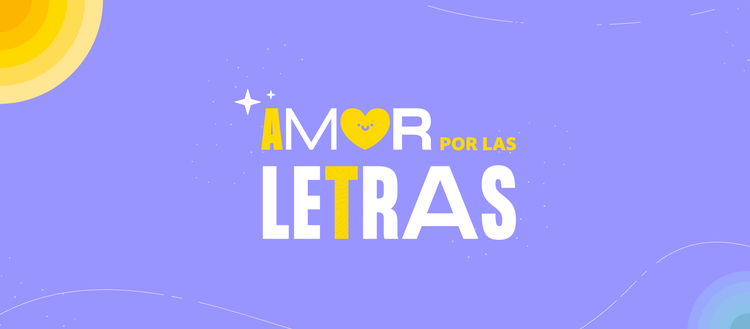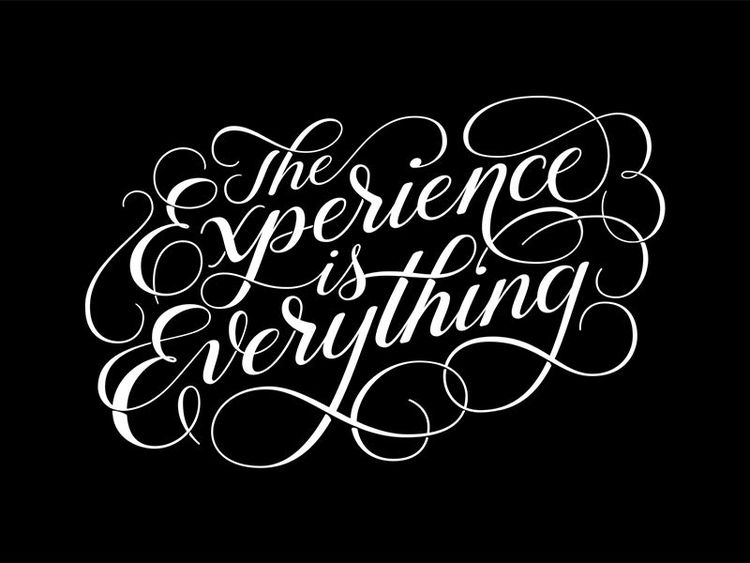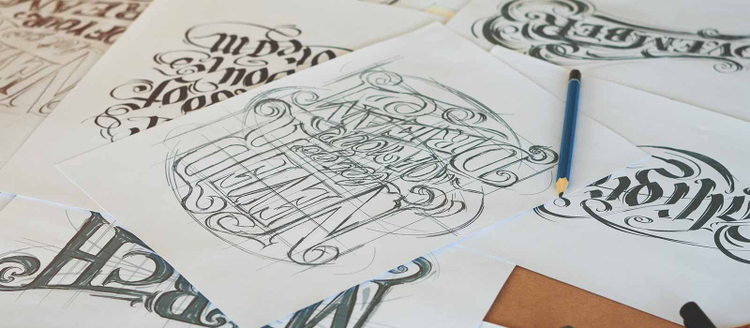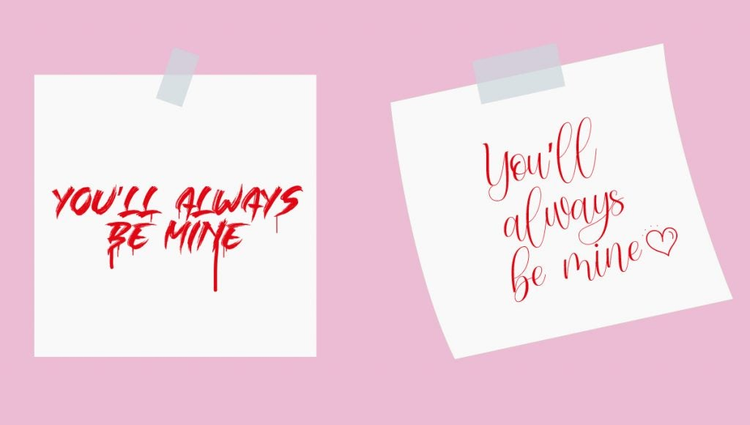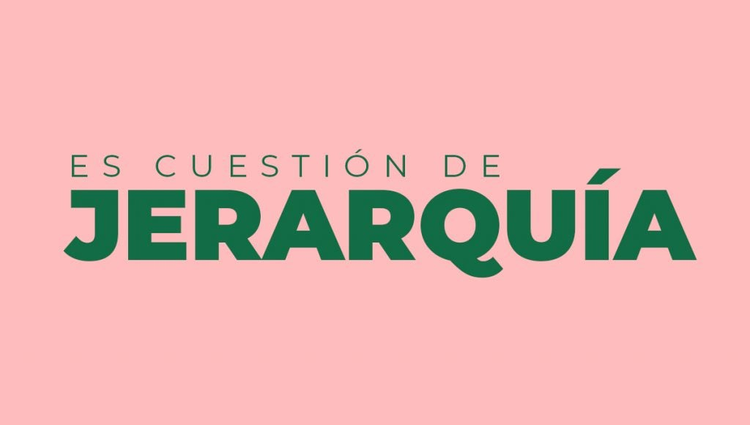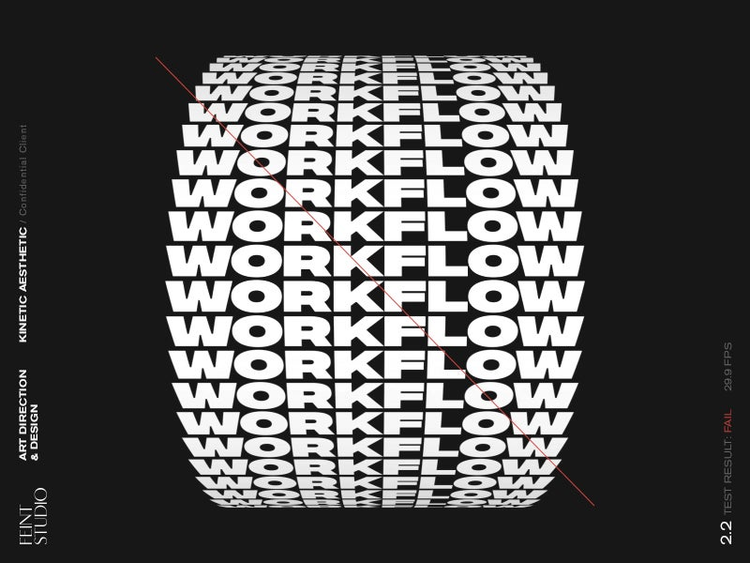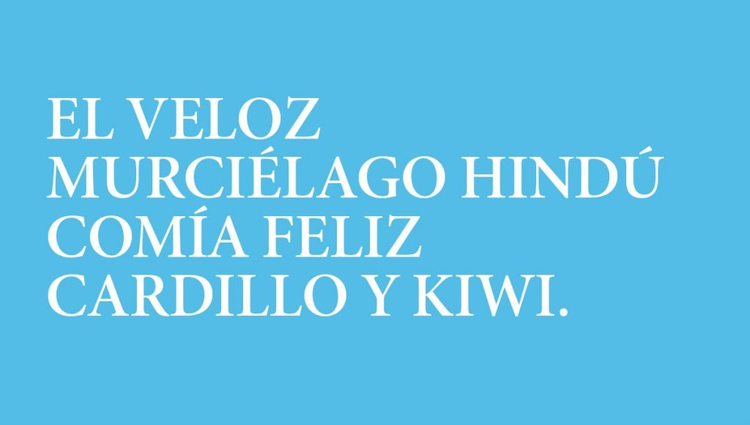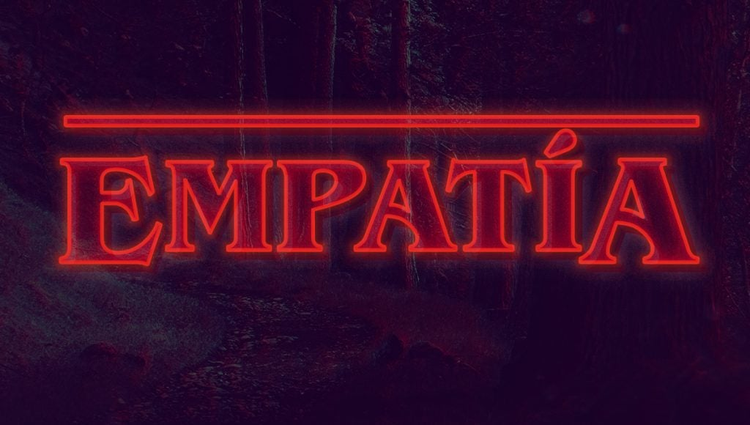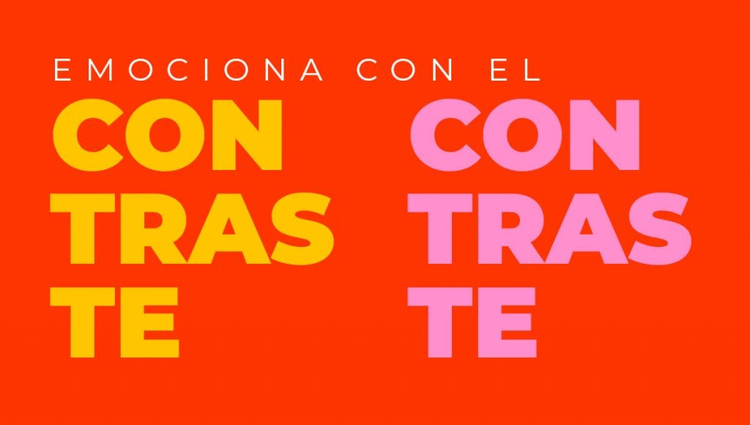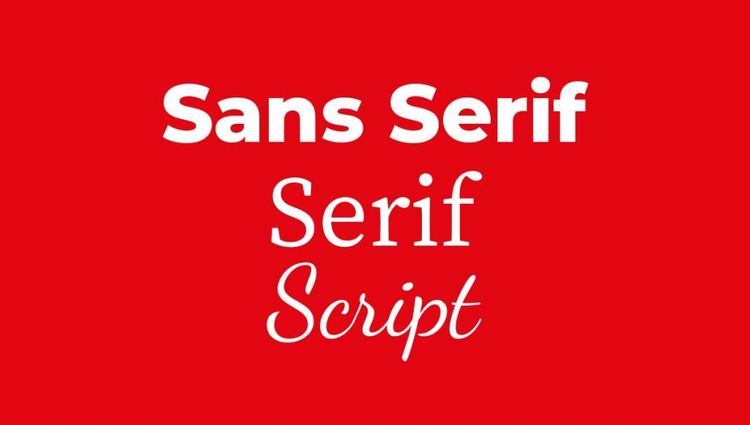
Sabemos que eres de los que descarga cuanta fuente ve por ahí gratis, por si algún día lo necesitas y lo único que has logrado es pasar horas y horas mirando cuál queda mejor, tráete un cafecito que aquí tenemos la solución para ahorrarte esos minutos de la mano de .
Nos gustaría empezar explicando por qué las fuentes de son importantes para los diseños, pero es mejor que lo haga un meme:
En un dos por tres te lo contamos:
Serif: la que tiene un trazo adicional; sofisticada y florecida
Sans Serif: sin el trazo, sencillita. Sans significa ‘sin’
Script: de trazo exclusivo, como letra cursiva
Para que cualquier diseño sea realmente efectivo, hay que entender muy bien a quién va dirigido. No puedes hablar de dinosaurios a niños de 3 años de la misma forma que le hablas a un experto paleontólogo.
- Genera confianza a través del diseño clásico de las fuentes Serif.
- Si quieres verte moderno, innovador o sencillo las tipografías Sans serif son lo tuyo.
- Vuelve romántico y caprichoso -solo algunas frases- tus diseños usando fuentes Script.
Puedes tener muchas fuentes gratis pero de nada sirve si no eres empático con el público. Sé uno con tu audiencia.
The experience is everything Rick Shaffer
Sí, sí, todo es importante peeeeero cuando todo es importante, realmente nada lo es. Organiza la información, ¿cuál es el mensaje principal? ese debería ir en una fuente más grande. Si tú no eliges la información destacada, tu ojo sí.
No todas las fuentes se ven bien con todo, aprovecha algunas impactantes para mensajes cortos y unas sencillas para los párrafos.
Las fuentes de las letras son como un lienzo y puedes usarlas a tu antojo, aprovecha sus formas, tamaños, estilos y crea una pieza única.
Por otro lado, vuelve tus diseños más emocionales con un toque artístico, para inspirarte no solo usa Pinterest, Behance, Dribbble sino explora las profundidades de las obras artísticas tipo Edward Hopper, Wong Kar Wai o las nuevas tendencias.
Muy bonito ¿pero ahí qué dice?
No dejes que la emoción te haga olvidar que lo importante es que se entienda; para obras conceptuales tenemos el MOMA.
Los títulos o encabezados pueden usar fuentes elaboradas y mayúsculas, y para los cuerpos algo sencillo.
Y por último, nuestro mayor secreto.
No olvides estos cinco consejos y diviértete en el proceso.